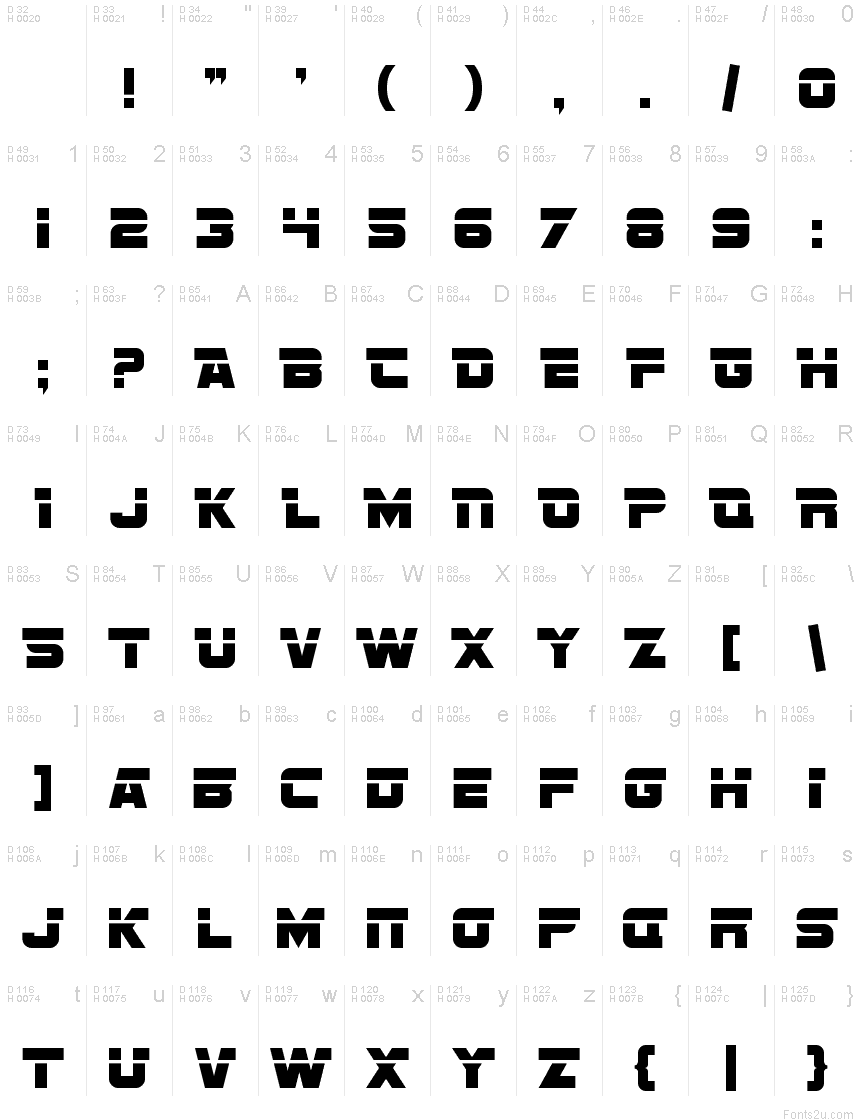
SF Sports Night Alt Upright, di ShyFoundry, è un font gratuito dal look futuristico e sportivo, con maiuscole larghe dalle forme fluide e dinamiche. Le lettere sembrano costruite con spessi blocchi modulari, mixando angoli retti decisi con profonde rientranze arrotondate che conferiscono al font un'atmosfera da arena notturna, tabelloni segnapunti e branding sportivo.
È perfetto dove una riga di testo breve richiede movimento e carattere: loghi e-sport, titoli per poster, grafiche ispirate alle divise sportive, titoli video e copertine di album o mixtape. Essendo un font gratuito, è ideale anche per gli overlay degli streamer e i volantini di eventi, soprattutto quando vuoi che le maiuscole sembrino scritte sportive personalizzate piuttosto che un neutro font display moderno.